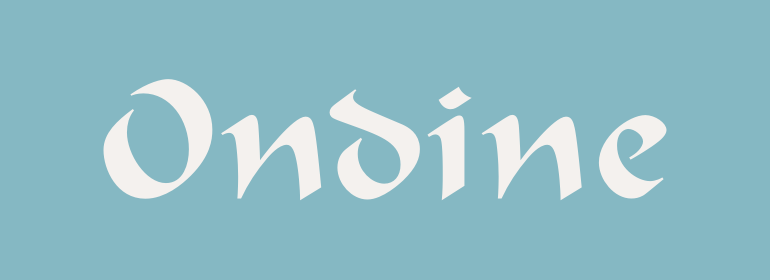
Ondine™
Ondine™,这款字体结构工整、笔画清晰,兼顾美观与易读性,适用于标题、正文、海报、包装、LOGO 等多种场景。字形优雅稳定,风格百搭耐看,适配日常排版与创意设计,让文字呈现更舒适、更具质感。Ondine™一笔一画,皆是细节,以均衡的比例、流畅的线条打造舒适视觉体验,字形端正大气,风格简约现代。无论是商业设计、品牌宣传还是日常排版,都能轻松驾驭,让文字更有格调与力量。Ondine™字体下载。
字体品牌: Linotype(Monotype) 设计师:Frutiger,Adrian 字体分类:书法体 字体属性:外文 字符集:Unicode 发布时间: 2018